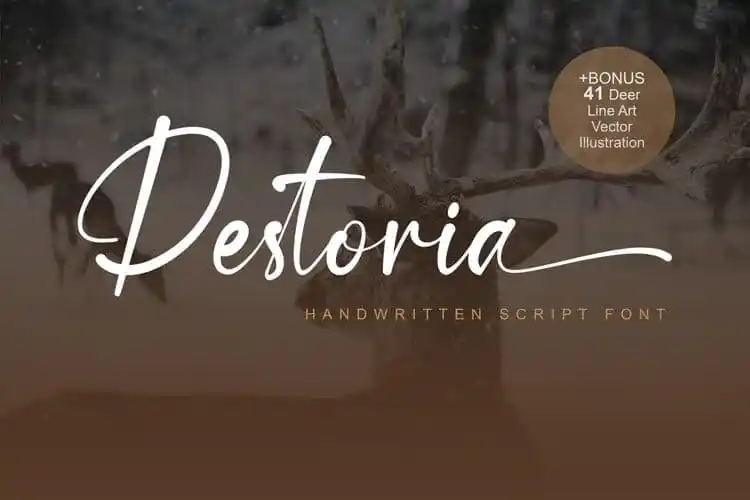
Destoria Calligraphy Font – Download Grátis
Aqui está uma descrição envolvente para a página de download da font ‘Destoria Calligraphy Font’: Nossa nova fonte de script, Destoria Calligraphy, oferece um toque natural e autêntico à sua tipografia, inspirada na escrita manual. Especialmente criada pelo designer lemonthe, esta font traz muitas alternativas estilizadas, ligações de caracol e swashes para explorar com as características OpenType, permitindo que você crie letrações com uma sensação natural. Perfeita tanto para festivais de casamento, embalagens de produto, cartões de aniversário quanto para postagem em redes sociais, a Destoria Calligraphy é perfeitamente adaptável para qualquer projeto gráfico. Não deixe de dar uma olhada nesta fonte que vai adicionar um toque especial ao seu próximo trabalho!